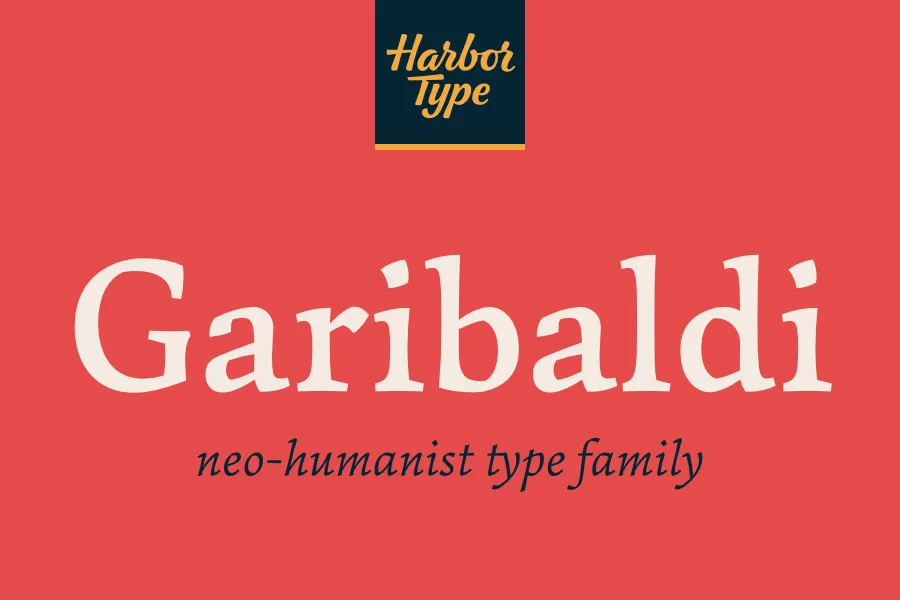
Garibaldi é uma fonte serif para texto baseada na calligrafia humanista. Com seu aspecto orgânico e a construção tradicional da tipografia romana, esta fonte oferece um toque familiar aos entusiastas da tipografia enquanto também permite experimentar novos estilos que respeitam o legado do design typeface. Através de sua assinatura 20 graus e contraste médio baseado em translasição e expansão, Garibaldi traz uma textura única que se assemelha a um traço elaborado com uma caneta grossa. Os serifs asimétricos adicionalmente adicionam detalhes interessantes às terminações da fonte. Este design foi desenvolvido pelo designer Hamilton para aqueles que desejam explorar os princípios básicos do humanismo na tipografia, oferecendo aos usuários uma maneira elegante de incorporar elementos históricos e modernos em seus projetos de layout.